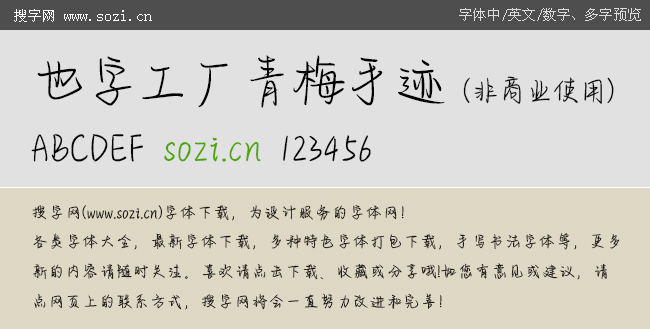
也字工廠青梅手跡
搜字網(wǎng)給大家提供一款也字工廠青梅手跡(非商業(yè)使用)中文字體下載,也字工廠青梅手跡是一款手寫書法字體,字體書寫流暢,字形自然大方,具有很好的視覺效果。適合應(yīng)用于書籍畫冊(cè)、海報(bào)、網(wǎng)頁設(shè)計(jì)等應(yīng)用(此字體為個(gè)人非商用版,商用可以聯(lián)系:官方網(wǎng)址:https://yefont.com/home,聯(lián)系方式:13798980448)。